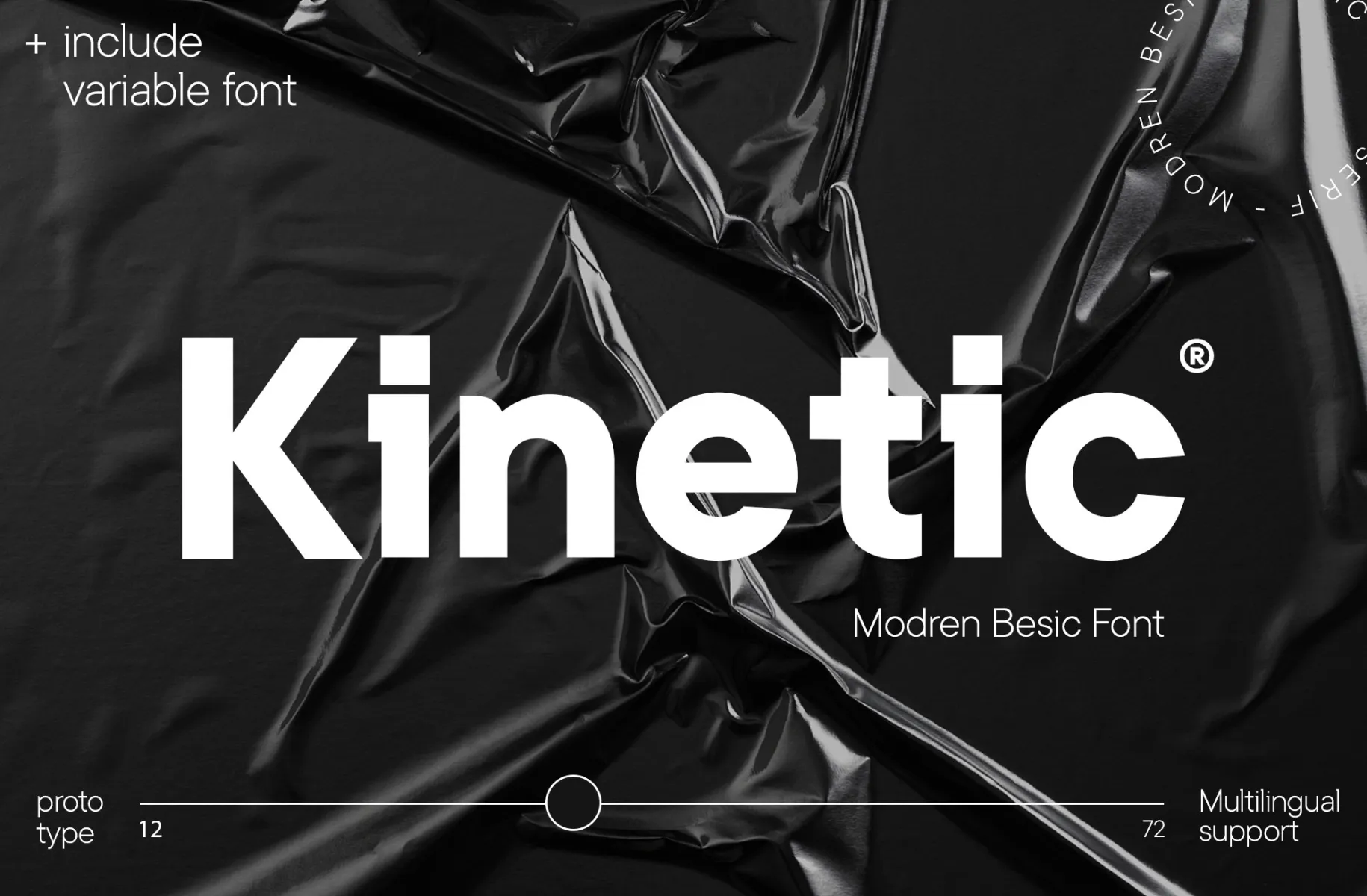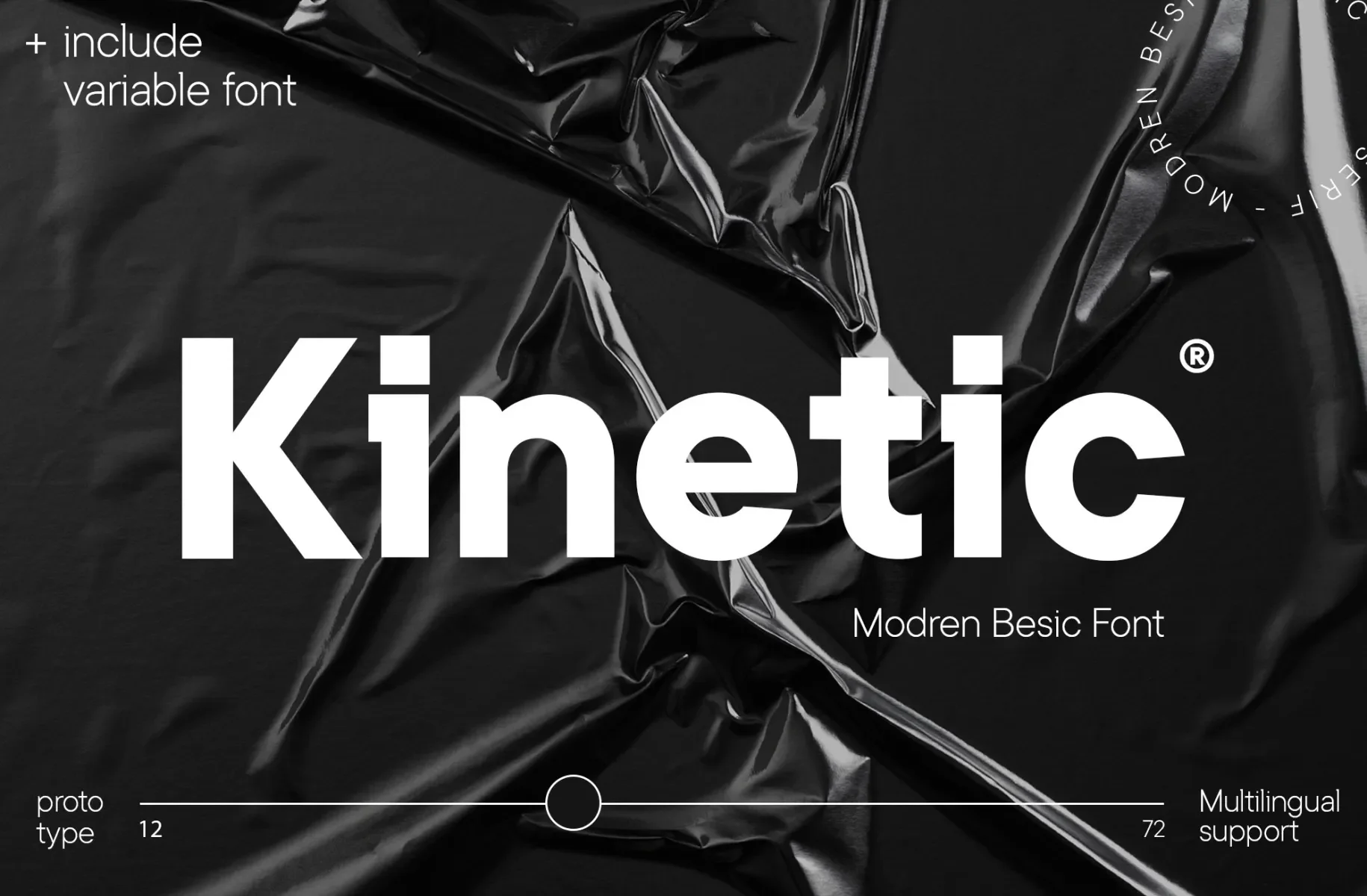
Kinetic
- это современный и крутой шрифт без засечек.
Его можно легко подобрать к невероятно большому набору проектов, поэтому добавьте его в свои творческие идеи и обратите внимание, как он выделяет их!